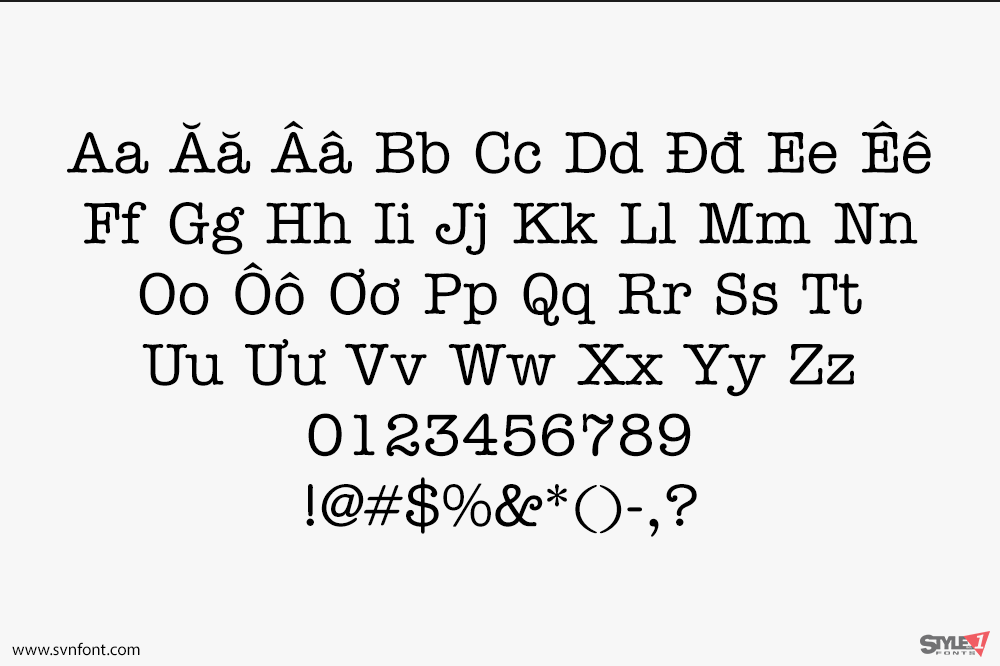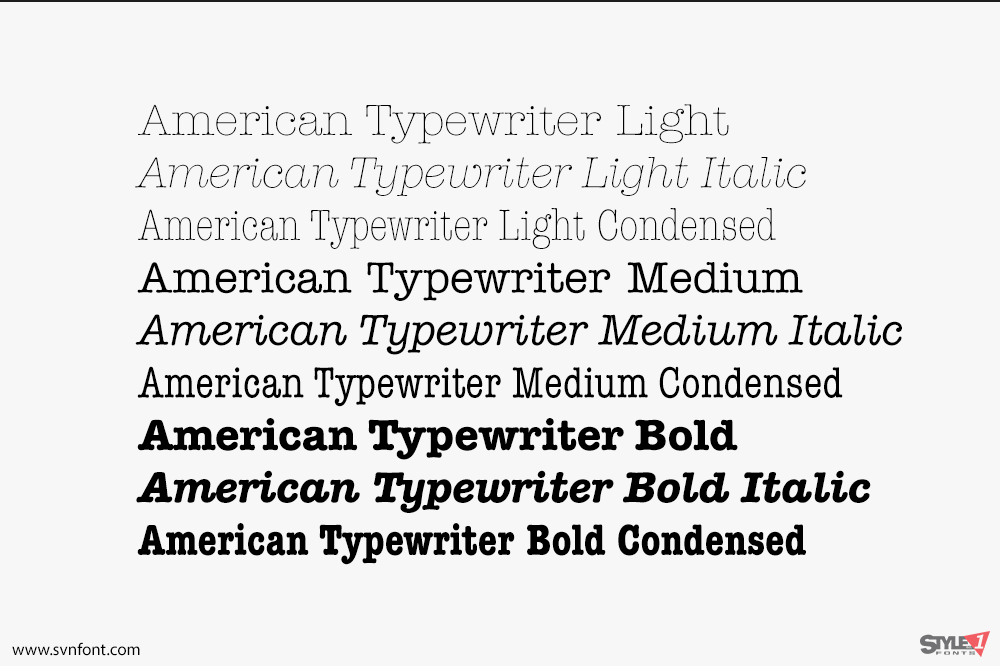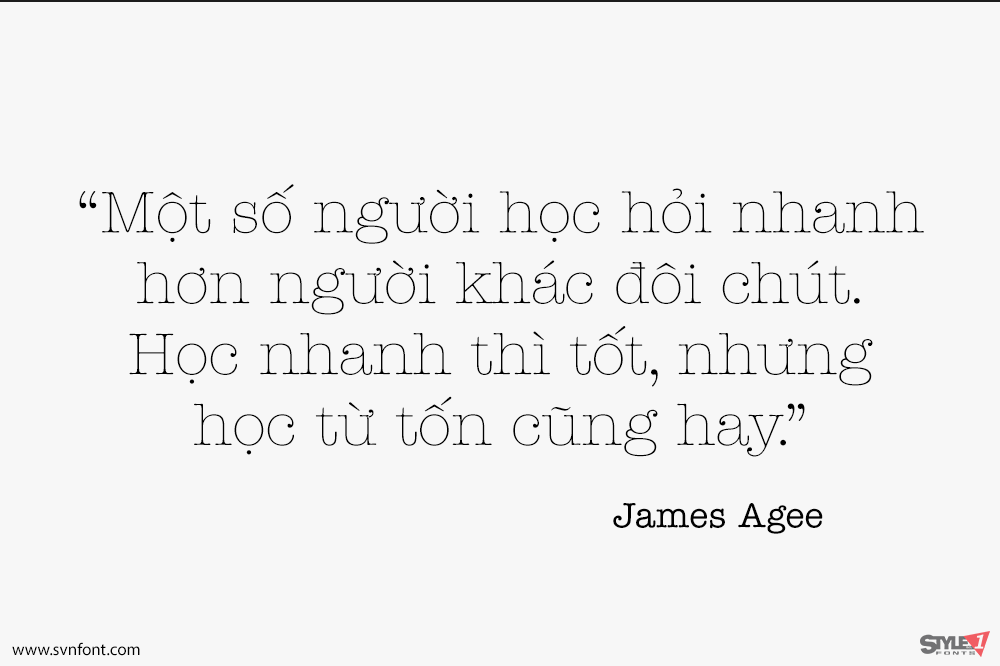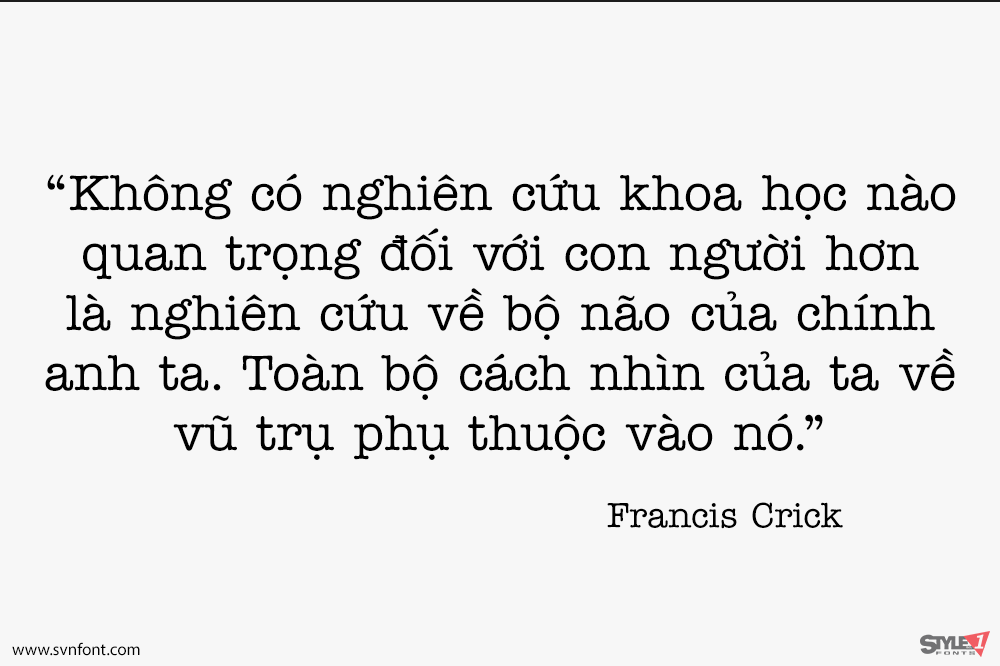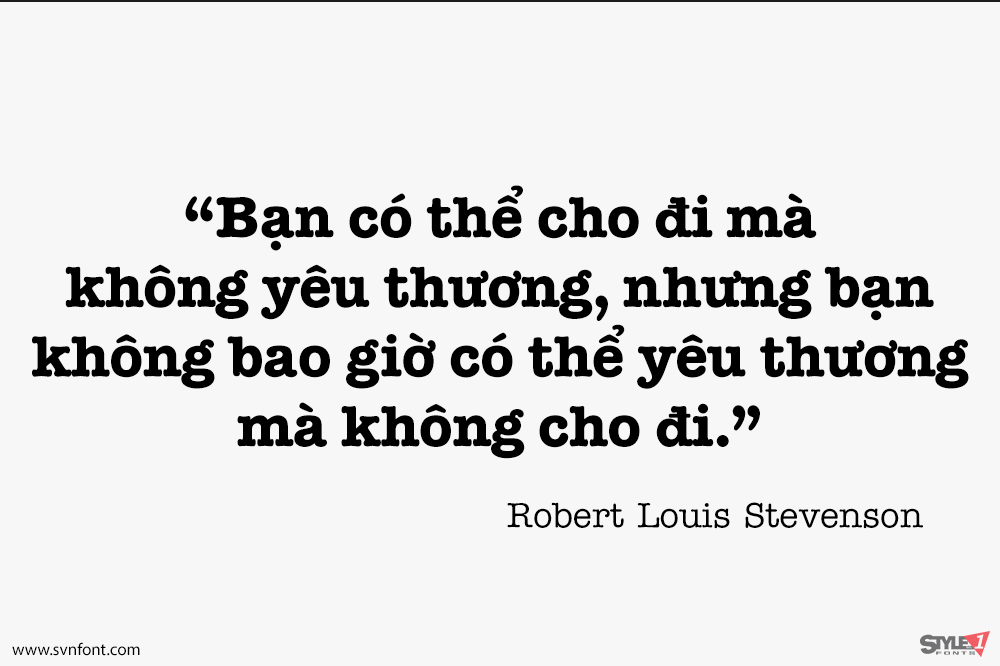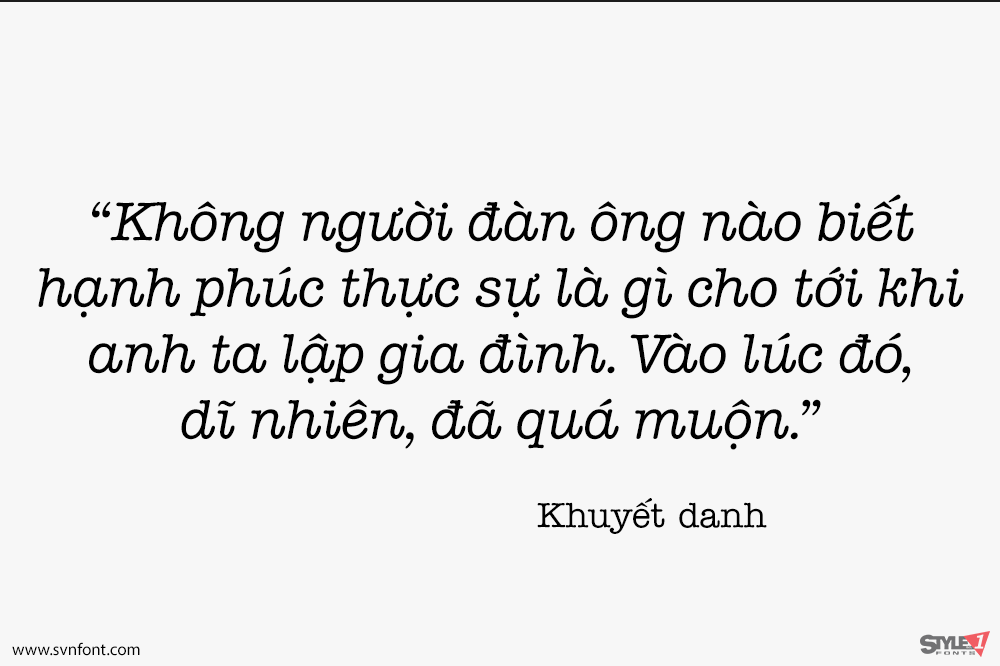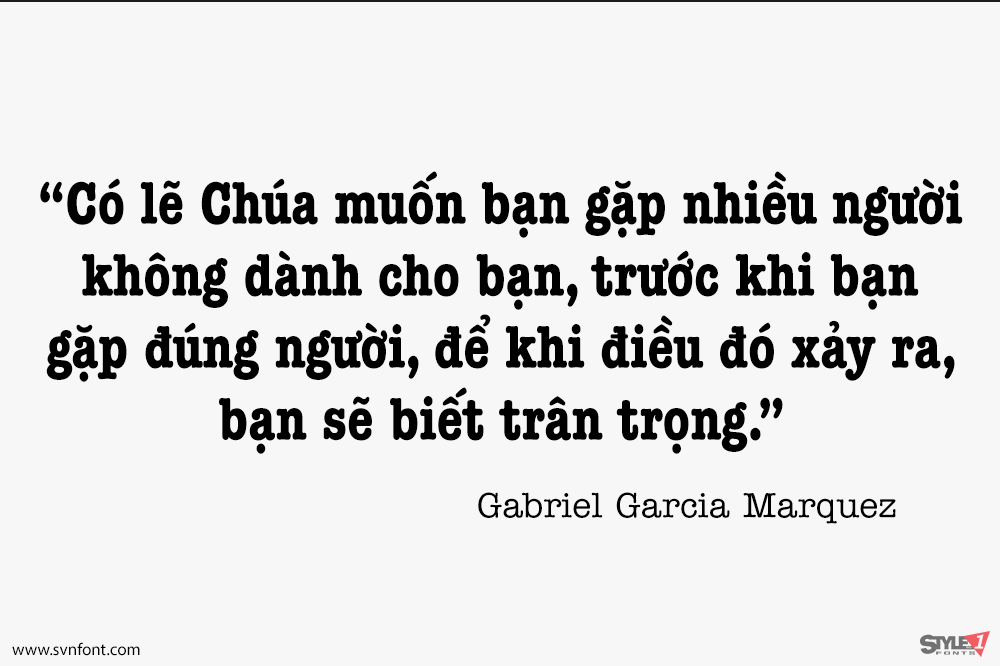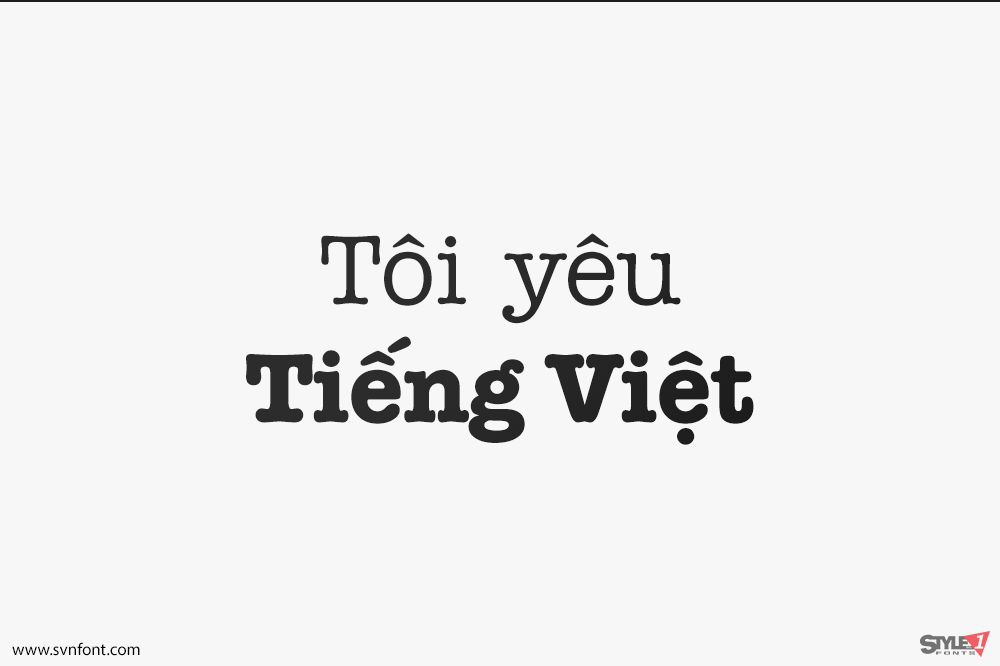
ITC American Typewriter được thiết kế bởi Joel Kaden và Tony Stan. Đây là một sự tôn vinh đối với phát minh đã định hình thói quen đọc và ý niệm về tính dễ đọc: máy đánh chữ. Là một sự dung hòa giữa sự cứng nhắc của người tiền nhiệm và những kỳ vọng của kỷ nguyên số, ITC American Typewriter vẫn giữ lại các hình dạng chữ cái điển hình của máy đánh chữ, mang lại cho phông chữ một chút hoài niệm.
Nhà thiết kế: Tony Stan, Joel Kaden
Nhà phát hành: ITC